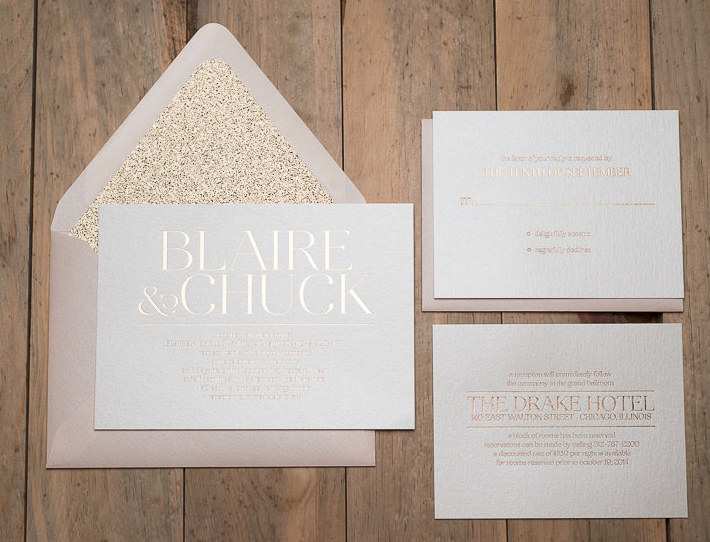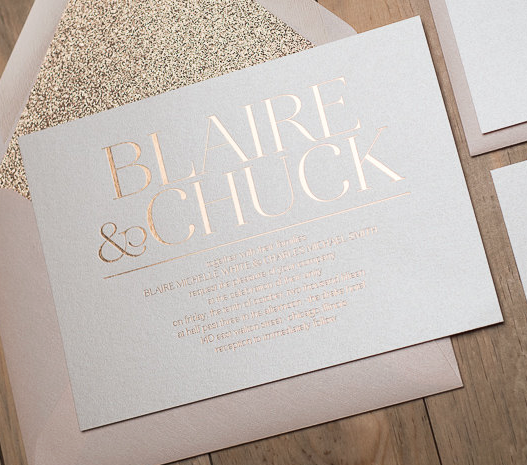
kann mir jemand sagen, was für eine Schriftart das hier ist?
Ich werde meine Hochzeitseinladungen selber machen und hätte gerne diese Schriftart.
Das "C" ist an den Enden rund.... das habe ich noch nirgends gesehen. Außerdem weiß ich nicht ob das & von der selben Schriftart ist.